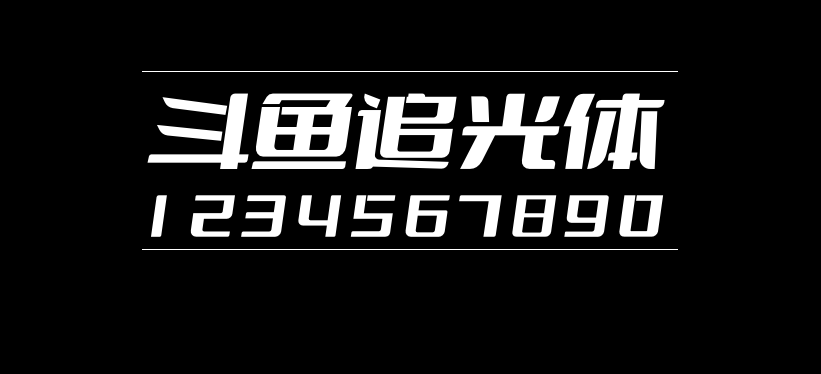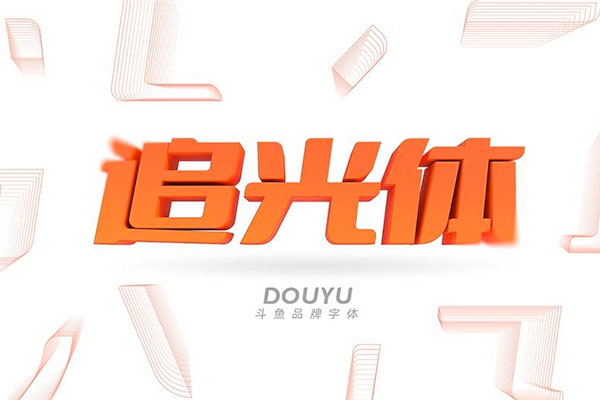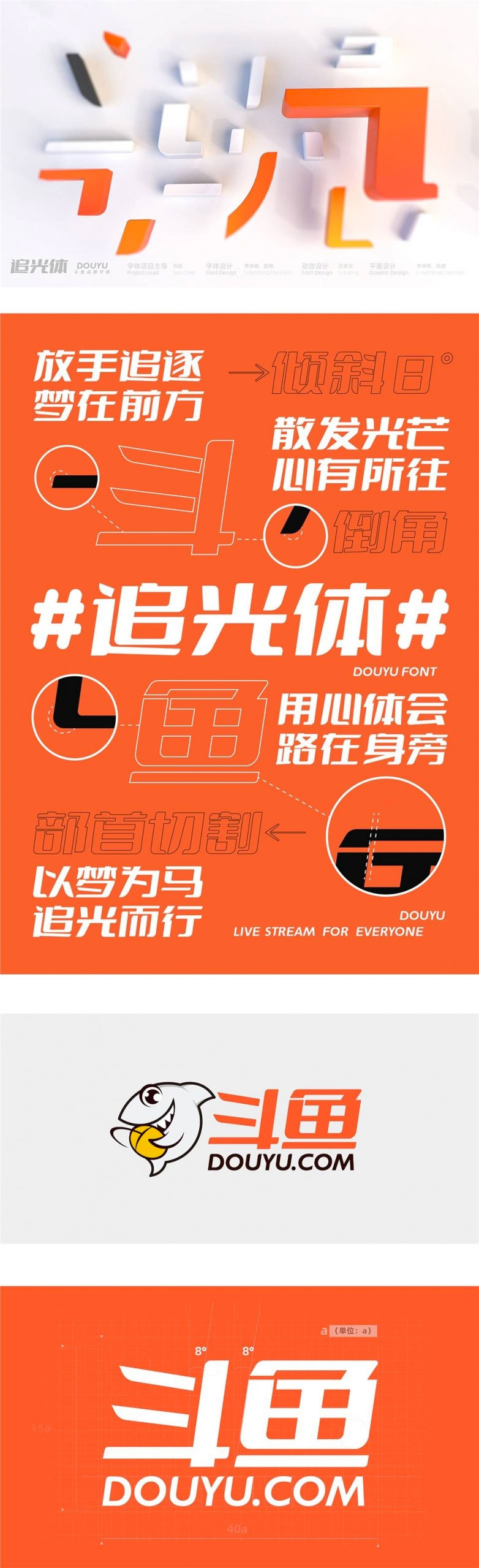
斗鱼追光体
斗鱼追光体(douyu font),是由斗鱼武汉研发部UED提供指导,品牌组设计成员主导设计的全新品牌字体。
斗鱼方面表示,斗鱼“追光体”!“追”是不断前行的步伐和勇气;“光”则是坚定的目标和梦想。该字体,向右8°倾斜,寓意着向前冲的态势;采用横细竖粗的原则,视觉上更趋平衡和谐;倒角设计惊艳,灵感取自LOGO中鲨鱼鱼鳍的拐角弧度。
很多人会问,斗鱼为什么要设计自己的字库,我们并非心血来潮,作为一个在国内知名的直播平台公司,我们需要统一的字体来发声,来表现企业自身的风格,并且向外界传递我们自己的品牌特质。我们也想统一公司内所有的子品牌标志与各项目的宣传形象,在视觉上用同一种声音来凸显斗鱼。我们希望用户想到斗鱼公司时,是会联想到一个具有活力、上进,且具有娱乐性质的科技型公司。我们设计团队也是秉承着这些,来设计这套字体。
斗鱼追光体是符合GB2312简体中文编码字符标准的专属品牌字体。是拥有一种标准版字重,包含6763个中文字符,100个西文及数字符号。随着斗鱼品牌场景的日益丰富,斗鱼追光体能逐渐适配平台的各种场景。
斗鱼追光体